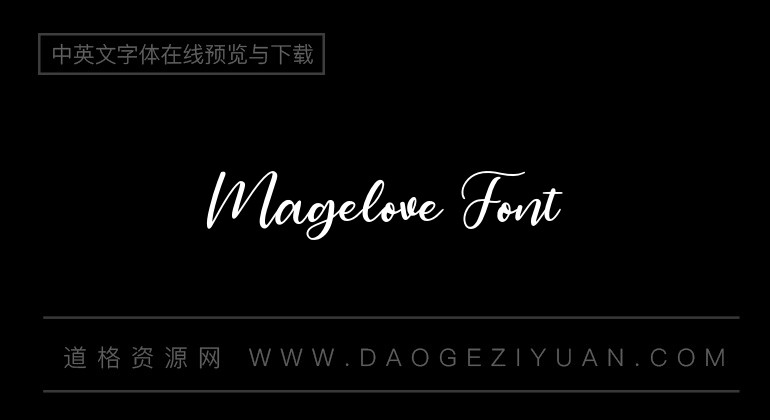
Magelove Font是一种手写风格的字体,它具有独特的轮廓和线条,可以用于设计许多不同风格的文本,例如书籍封面、海报、名片、广告等。它的手写风格使其看起来非常自然,也非常适合用于手工制作的项目以及手写笔记和信件。此外,Magelove Font也非常易于阅读,因为它的字母形状和间隔都很清晰。如果你正在寻找一种充满个性和艺术感的字体,Magelove Font绝对是一个不错的选择。内容介绍
Magelove Font是一款非常不错的手写艺术字体,具有很好的视觉感,适合于文化类的宣传设计、商业类品牌的广告和产品包装设计以及个性化文字排版等较多场景。